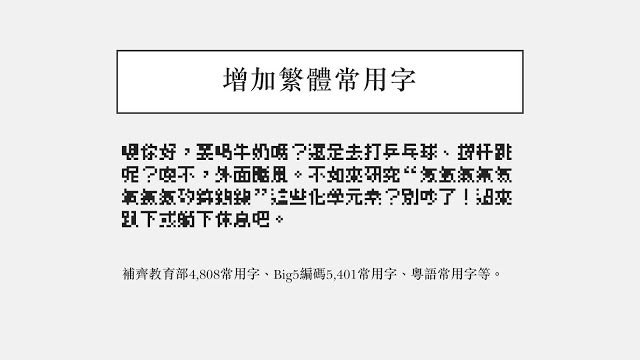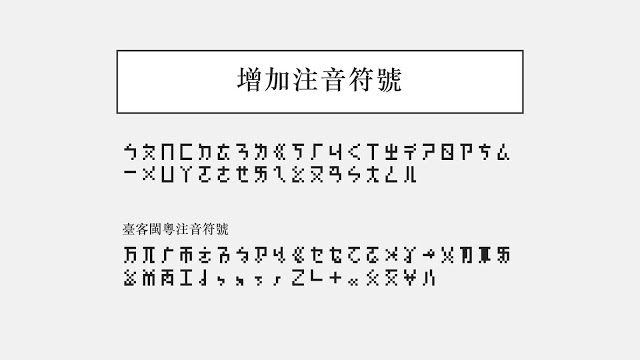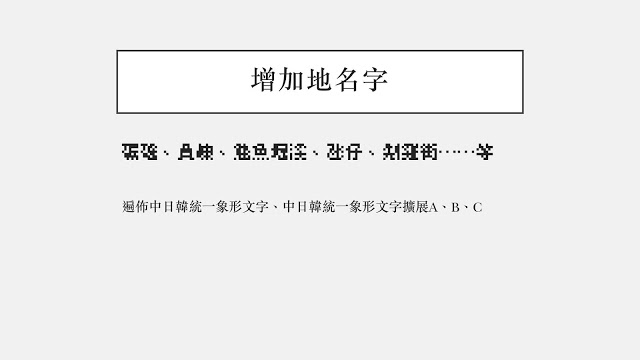
精品点阵体7×7 1.5
字体名称: 精品点阵体7×7 1.5
字体风格: 像素体
《精品点阵体7×7 (BoutiqueBitmap7x7) 》是一款基于美咲フォント改作的字型,目的为适合在繁体中文环境中使用。我们改正了一些标点符号、日本习惯写法、增加近2,500个字符,使字型使用更方便!
这是一款带有极强烈的点阵风格的字型,非常适合用在像素画、游戏相关主题等等。